【無料配布10種】Premiere Pro テロップ テキストスタイル|フォント同梱・商用利用OK
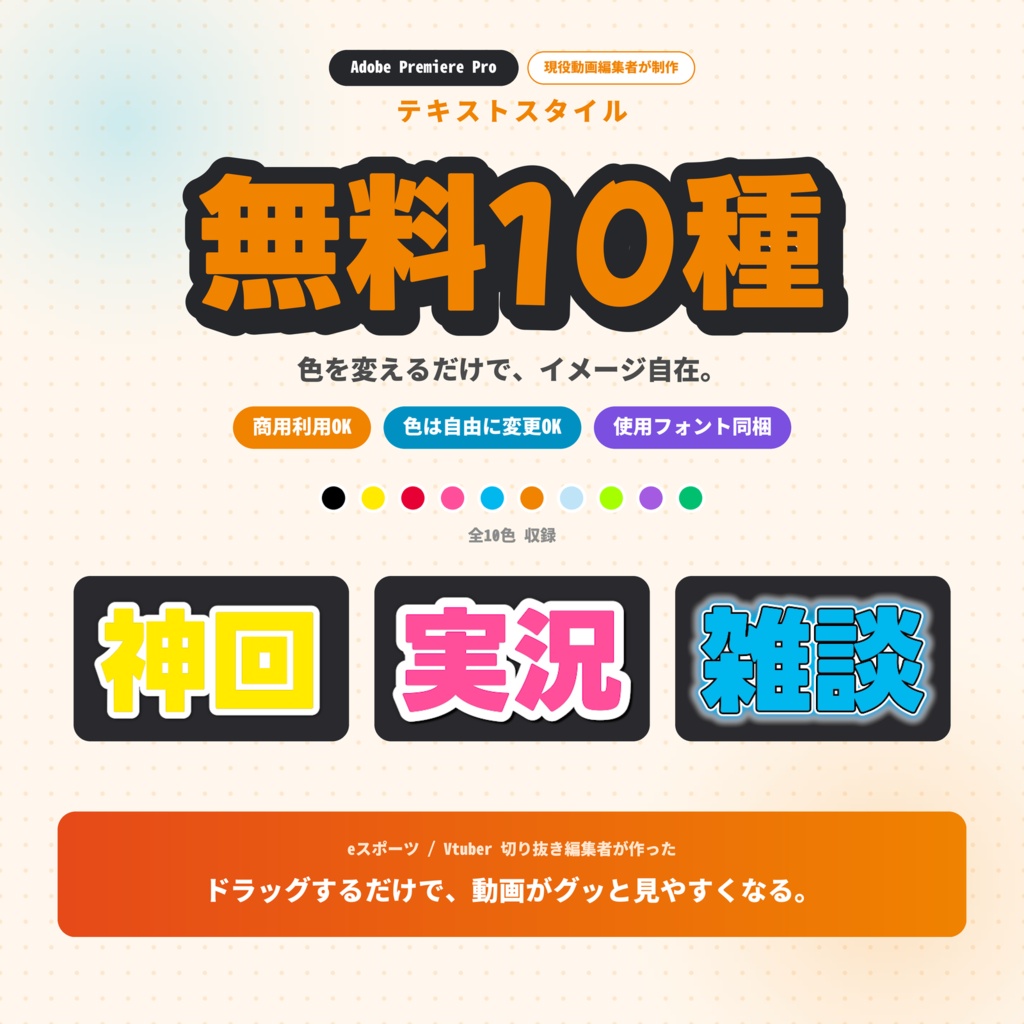
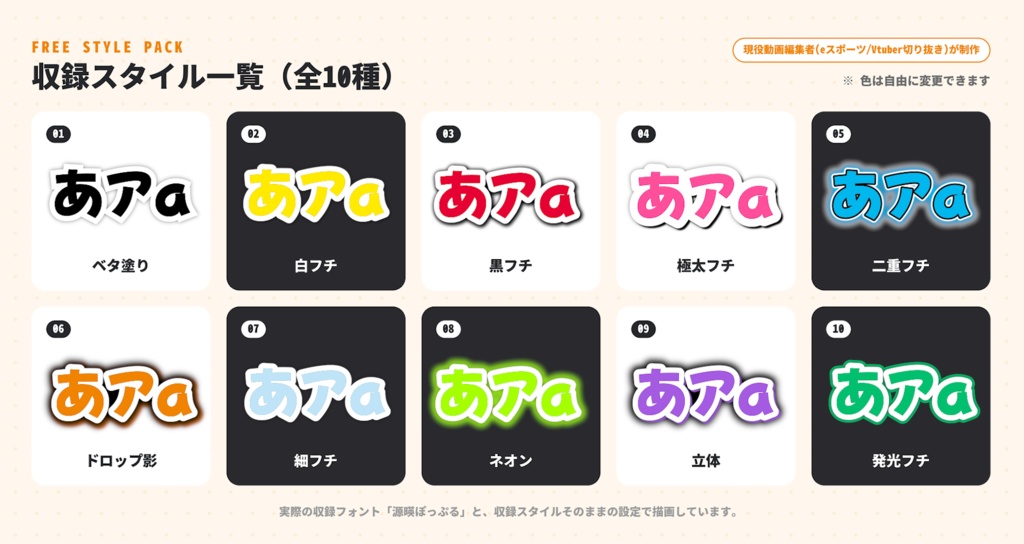
Premiere Pro で使えるテロップ用テキストスタイル10種の無料配布です。 使用フォントを同梱しているので、ダウンロードしてすぐ同じ見た目が出せます。 ■ 収録スタイル(全10種) 01 通常_ベタ塗り_黒 フチなしの基本形。明るい映像・白背景向け 02 通常_白フチ_黄 バラエティ/ゲーム実況の定番 03 通常_黒フチ_赤 明るい背景でも埋もれない 04 強調_極太フチ_桃 ツッコミ・叫びに 05 強調_二重フチ_水 白+黒の二重フチ。どんな背景でも読める 06 強調_ドロップ影_橙 影を落として立たせる強調枠 07 小声_細フチ_薄水 ささやき・心の声・補足に 08 演出_ネオン_黄緑 発光させたネオン風。ホラー/ゲーム演出に 09 演出_立体_紫 押し出しのある立体表現 10 見出し_発光フチ_緑 太フチ+発光。見出し・章タイトルに 色は適用後に「塗り」を変えるだけで自由に変更できます。 ■ 同梱物 ・無料版10種.prtextstyle(本体) ・見本プロジェクト(10種が3秒ずつ順に再生されます/全30秒) ・使用フォント「源暎ぽっぷる」本体 ・フォントライセンス全文(SIL Open Font License 1.1) ・はじめにお読みください.txt ■ 使い方(3ステップ) 1. 同梱のフォントをインストール 2. Premiere Pro でプロジェクトを開く 3.「ファイル」→「読み込み」から .prtextstyle を選ぶ テキストクリップを選択し、スタイルをダブルクリックで適用されます。 ■ 動作環境 ・Adobe Premiere Pro 2026(v26.3)で作成・動作確認 ・Windows / macOS 両対応 ・見本プロジェクト(.prproj)は、Premiereの仕様上、これより古い バージョンでは開けない場合があります。本体の .prtextstyle は そのままお試しいただけます。 ■ ご利用について ○ 個人・法人を問わず動画制作に使用可/収益化動画も可/改変可 × ファイル自体の再配布・販売/素材集としての二次配布 ■ ご注意 アニメーション(動き)は含まれません。文字の見た目のみです。 ■ 完全版について 現在完全版を準備中です。 公開のお知らせは @neju_xx でお伝えします。 ■ お問い合わせ BOOTHのメッセージ、または @neju_xx まで。